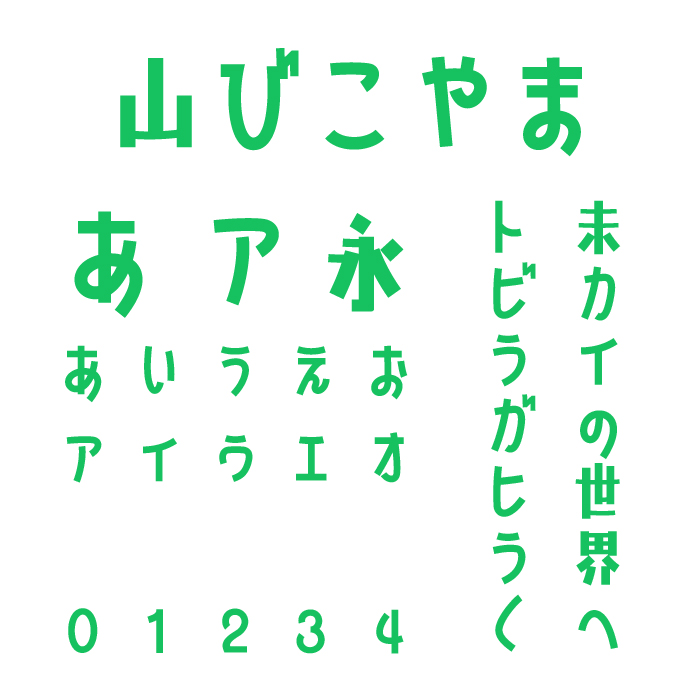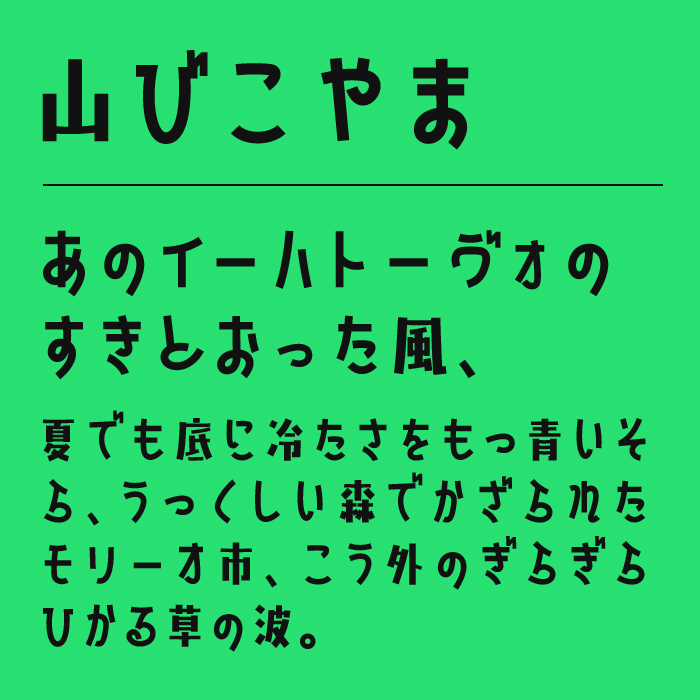
山びこやまフォントは、懐かしさを感じるような、どこかレトロ的で温かいテイストがにじむデザインフォントです。
ゆるやかに丸められたフォルムと、少しだけ傾いたラインが、人の手で描いたような、親しみある素朴で自然なトーンを作り出しているフォントです。
全体のバランスが整っており、ゆるさと安定感を両立させた設計で、ナチュラル・ほのぼのとした世界観の中で、ぬくもりを演出するのに最適なフォントです。
収録文字は、ひらがな・カタカナ・数字・記号が収録。